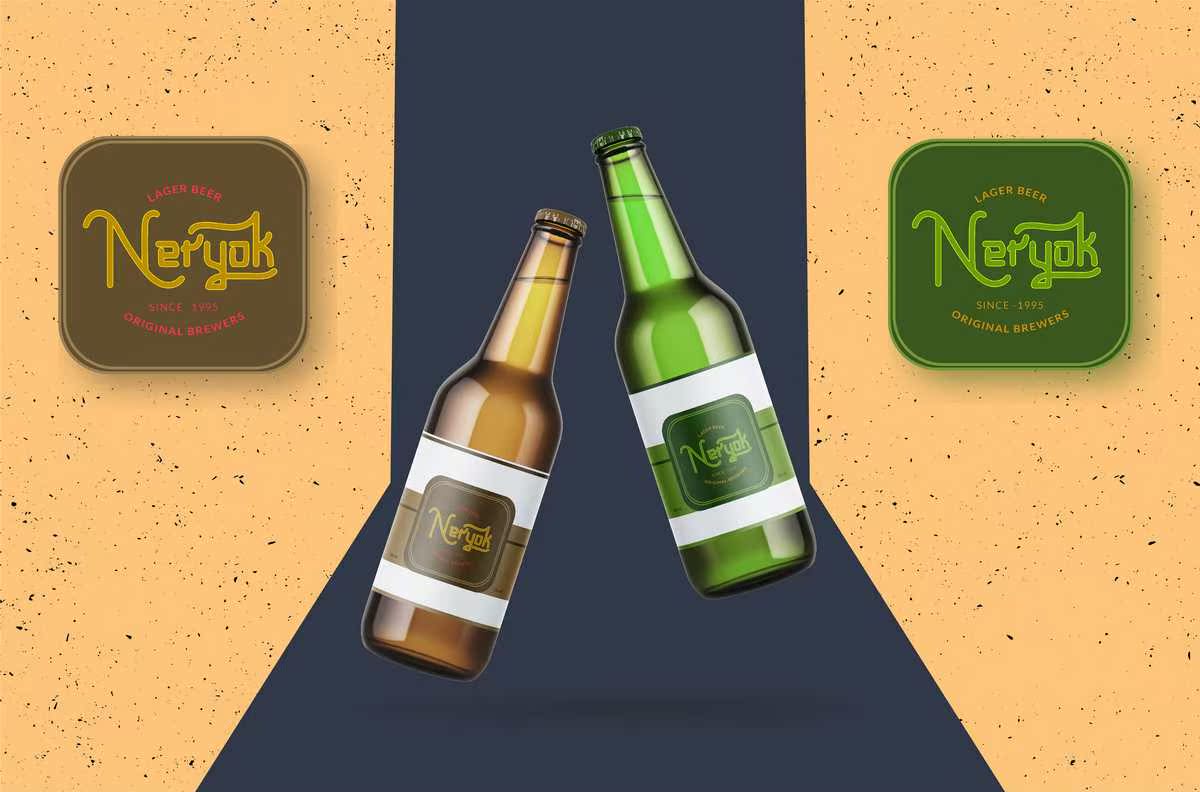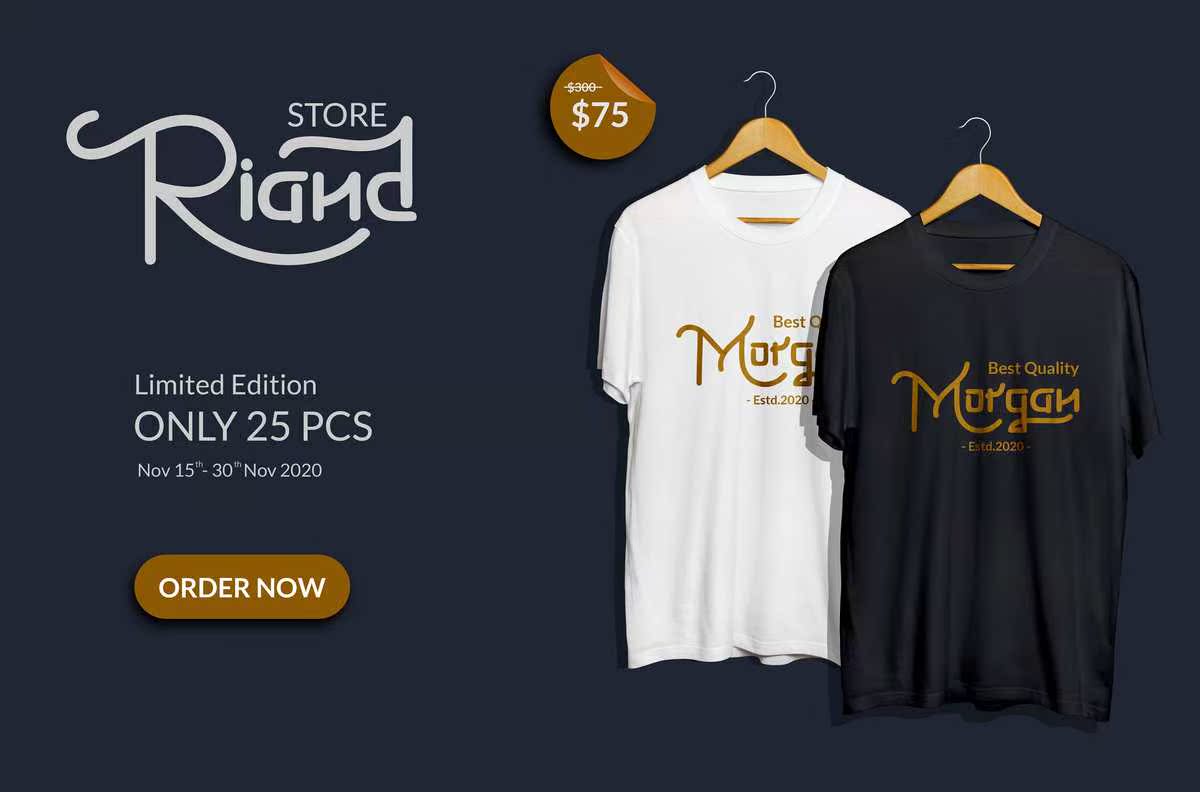
简介Glorist Tais MaintageMonoline字体。这款字体采用了一种在不断增长的趋势下始终保持不变的字体样式。这款单字体字体每个字母都有一个突出的特征,因此适合任何工作类型的需要。因此,这款字体可以让您的产品看起来既漂亮又酷。它非常适合需要时尚、标题、标识、服装等字体的用户,Marchandise、branding、packaging、Advertision等。简介Glorist Tais MaintageMonoline字体。此字体创建时使用的字体样式始终符合不断增长的趋势。此单一字体字体每封信都有一个巨大的字符,SOI适用于任何类型的工作。SOI直接具有此功能,使您的产品看起来既美观又酷。它们非常适合需要时尚、标题、标识、服装、马赛克、品牌、包装、广告等字体的用户